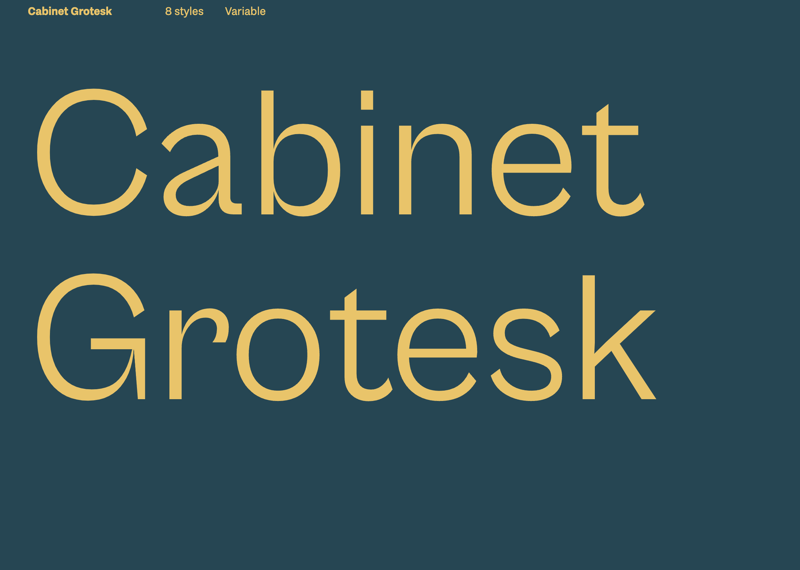
Cabinet Grotesk: Free Sans font in 8 Schnitten
Cabinet Grotesk ist eine beeindruckende kostenlose Schriftart, die von der Indian Type Foundry vertrieben wird. Es handelt sich dabei um eine moderne serifenlose Schriftart, die aufgrund ihrer einzigartigen Formen und Kontraste von anderen Grotesk-Schriftarten hervorsticht. Sie ist in 8 Gewichten von dünn bis schwarz erhältlich und behält dennoch ein einheitliches Design bei.
Durch Verwendung schwererer Gewichte wird der Strichkontrast in den Buchstabenformen aufgrund der Strichverbindungen am deutlichsten hervorgehoben und sorgt für einen einzigartigen Look. Bei Cabinet Grotesk sind die Ziffern proportional und entsprechen der Höhe der Großbuchstaben.
Cabinet Grotesk Weights